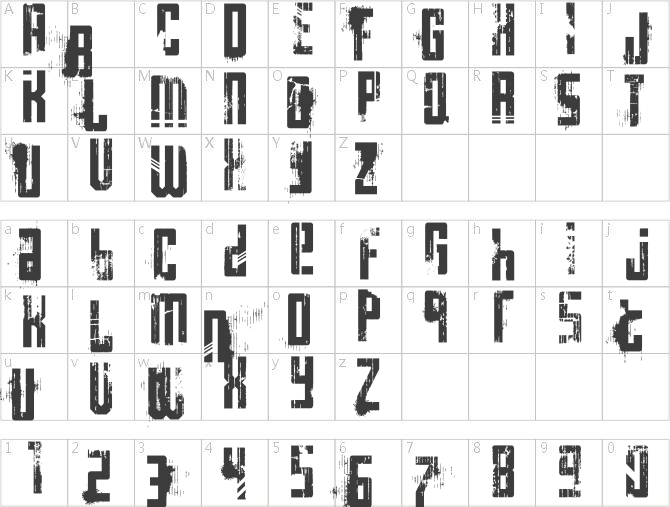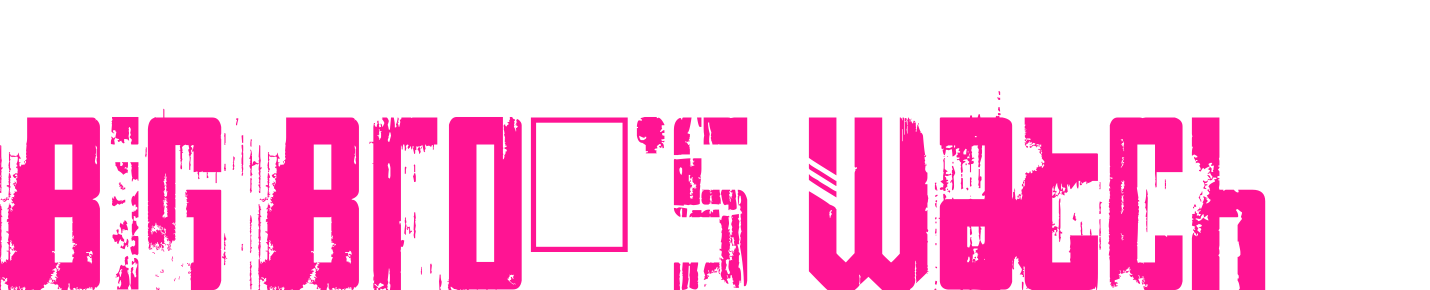
Big Bro_'s Watch 詳情頁
字體名稱: Big Bro
Big Bro_'s Watch
Big Bro_'s Watch字體字庫是一款讓人賞心悅目、百看不厭的英文字體,適合各類廣告和產品包裝設計應用,字體大小0.16MB,格式為ttf字體,上傳用戶是373790005,作者/版權方為未知